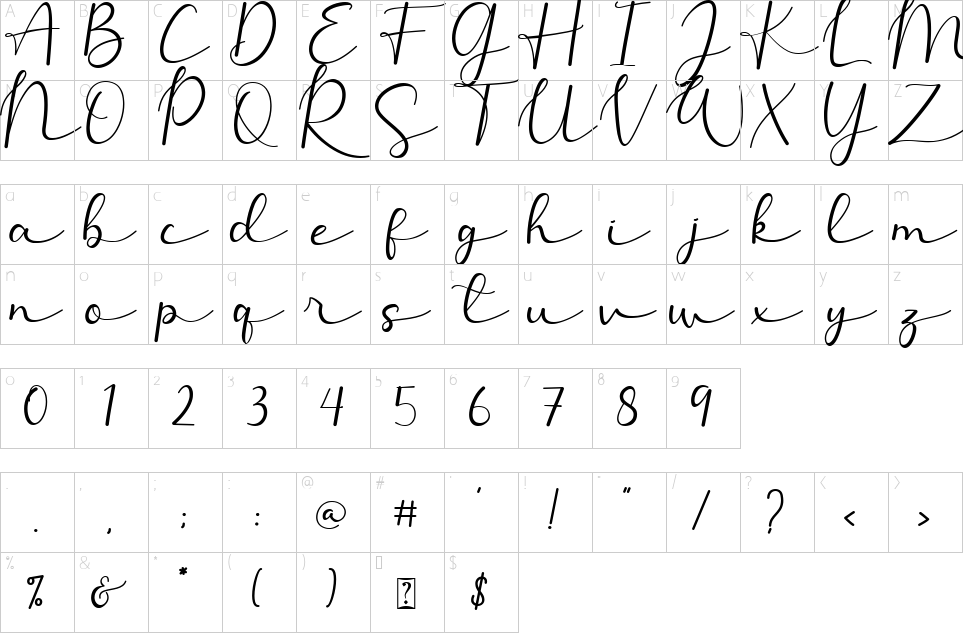
A fonte Allesia é uma adição perfeita para qualquer projeto de design gráfico. Desenvolvida pela AEN Creative Studio, Allesia oferece uma variedade de tamanhos e estilos, permitindo que você personalize o texto de várias maneiras. Seja para um logotipo, um layout de newsletter ou até mesmo um projeto web, Allesia atende a essas necessidades, oferecendo uma escolha versátil e elegante para cada projeto. O designer não informado mantém a qualidade do design, garantindo que seja uma fonte de alta qualidade disponível gratuitamente. Seja você um designer iniciante ou um profissional experiente, a Allesia é uma fonte que vale a pena experimentar, disponível para download para Windows e Mac.